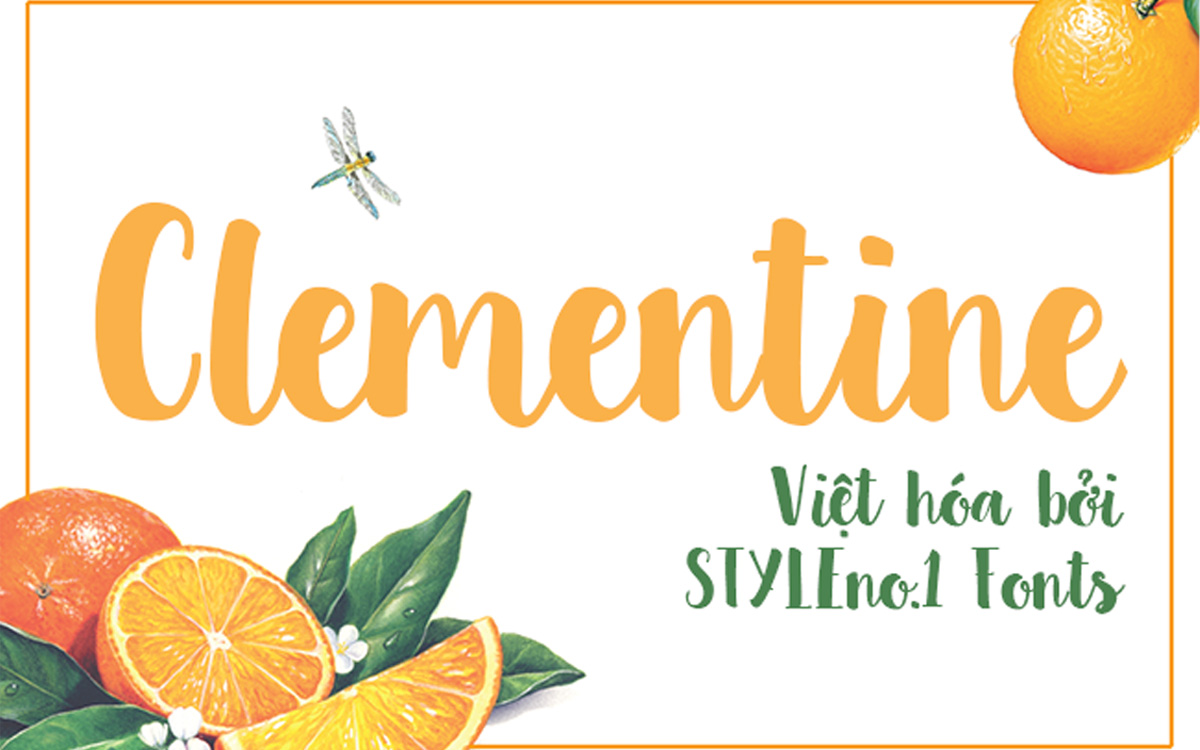
Font chữ vui vẻ, dễ thương, hoạt hình cho lĩnh vực trẻ em, đồ ăn, fodd, cute SVN-Clementine
Trong thế giới thiết kế đồ họa hiện đại, việc lựa chọn một font chữ phù hợp đóng vai trò quyết định đến cảm xúc và thông điệp mà thương hiệu muốn gửi gắm đến khách hàng. Nếu bạn đang tìm kiếm một làn gió mới tràn đầy sức sống, ngộ nghĩnh và gần gũi cho các dự án của mình thì SVN-Clementine chính là sự lựa chọn không thể tuyệt vời hơn. Với phong cách hoạt hình vui nhộn, nét chữ mềm mại cùng bản Việt hóa chỉn chu, bộ font này hứa hẹn sẽ biến mọi ý tưởng thiết kế trở nên nổi bật và đầy sức hút.
Font Chữ Vui Vẻ, Dễ Thương, Hoạt Hình Cho Lĩnh Vực Trẻ Em, Đồ Ăn (Food) – Bộ Ký Tự Cute SVN-Clementine Việt Hóa
Phong Cách Thiết Kế Bo Tròn Ngộ Nghĩnh Mang Đến Cảm Giác Vui Vẻ Tự Nhiên
Font chữ SVN-Clementine sở hữu đường nét bo tròn mượt mà, loại bỏ hoàn toàn sự cứng nhắc của các phông chữ hình học truyền thống. Sự kết hợp tinh tế giữa phong cách vẽ tay thủ công (hand-drawn) và hiệu ứng nảy (bouncy baseline) tạo nên nhịp điệu thị giác vô cùng sinh động. Mỗi ký tự trong bộ font đều được chăm chút tỉ mỉ với khoảng hở và độ dày nét hài hòa, mang đến cảm giác thân thiện, tươi vui và tràn đầy năng lượng tích cực. Phong cách hoạt hình đáng yêu này không chỉ thu hút thị giác của trẻ em mà còn dễ dàng chiếm được cảm tình của bất kỳ ai yêu thích sự ngọt ngào, gần gũi.
Điểm đặc biệt của SVN-Clementine nằm ở khả năng tạo điểm nhấn thị giác cực mạnh ngay cả khi xuất hiện ở kích thước lớn trên các bảng hiệu hay tiêu đề chính. Nét chữ đậm vừa phải cùng các góc bo tròn mượt mà giúp nội dung nổi bật mà không gây cảm giác nặng nề. Nhờ sự linh hoạt này, nhà thiết kế có thể dễ dàng phối hợp font với nhiều hiệu ứng màu sắc rực rỡ, đường viền (stroke) hoặc hiệu ứng đổ bóng (drop shadow) để tạo nên những sản phẩm truyền thông độc đáo, bắt mắt.
Việt Hóa Trọn Bộ Chuẩn Xác – Tối Ưu Cho Sáng Tạo Nội Dung Tiếng Việt
Một trong những rào cản lớn nhất khi sử dụng các font chữ cute quốc tế là lỗi hiển thị tiếng Việt như bị mất dấu, lệch dấu hoặc các ký tự có dấu bị biến dạng làm mất tính thẩm mỹ của thiết kế. SVN-Clementine đã được việt hóa hoàn chỉnh và cẩn thận đến từng chi tiết nhỏ nhất. Các dấu thanh (sắc, huyền, hỏi, ngã, nặng) và dấu mũ (â, ê, ô, ơ, ư) đều được điều chỉnh vị trí chuẩn xác, giữ nguyên tỉ lệ và tinh thần vui tươi nguyên bản của tác giả gốc.
Việc việt hóa chuẩn chỉnh giúp các nhà thiết kế đồ họa, content creator và marketer tại Việt Nam dễ dàng sáng tạo nội dung mà không gặp bất kỳ trở ngại nào về mặt kỹ thuật. Bạn có thể tự tin áp dụng SVN-Clementine vào các dự án commercial, từ viết slogan ngắn gọn, giật gân cho đến việc làm tiêu đề bài viết trên mạng xã hội, đảm bảo sự chuyên nghiệp và tính thẩm mỹ đồng nhất trên mọi ấn phẩm.
Giải Pháp Typography Lý Tưởng Cho Lĩnh Vực Trẻ Em Và Giáo Dục Mầm Non
Trẻ em luôn bị thu hút bởi những hình ảnh vui nhộn, nhiều màu sắc và những đường nét chữ ngộ nghĩnh. SVN-Clementine đáp ứng hoàn hảo yêu cầu tâm lý học thị giác này nhờ vẻ ngoài đậm chất cartoon hoạt hình. Bộ font chữ này là giải pháp typography hàng đầu cho các thương hiệu đồ chơi, thời trang trẻ em, sách truyện tranh, bìa sách giáo trình mầm non, bảng cửu chương, tập tô màu hay các khu vui chơi giải trí dành cho gia đình.
Bên cạnh đó, các ấn phẩm sự kiện như tiệc sinh nhật, Tết Trung Thu, Quốc tế Thiếu nhi hay lễ hội trường học khi ứng dụng font SVN-Clementine đều mang lại không khí hân hoan, rộn rã. Sự xuất hiện của bộ phông chữ dễ thương này trên bao bì sản phẩm mẹ và bé không chỉ gây chú ý mạnh mẽ với các bé mà còn tạo cảm giác an toàn, thân thiện và đáng tin cậy đối với các bậc phụ huynh.
Bứt Phá Sáng Tạo Trong Lĩnh Vực Đồ Ăn, Thức Uống (Food & Beverage – F&B)
Không chỉ dừng lại ở thế giới của trẻ thơ, SVN-Clementine còn phát huy sức mạnh vượt trội trong ngành ẩm thực và dịch vụ ăn uống. Nhờ kiểu dáng tròn trịa, mập mạp gợi liên tưởng đến những chiếc bánh quy bơ ngọt ngào hay những viên kẹo dẻo rực rỡ, font chữ này cực kỳ thích hợp cho các thương hiệu tiệm bánh (bakery), quán trà sữa, cửa hàng kem, quán ăn vặt và thực phẩm đóng gói. Nét chữ vui nhộn giúp kích thích vị giác và tạo nên cảm giác thèm ăn một cách rất tự nhiên.
Các designer có thể dễ dàng ứng dụng SVN-Clementine để thiết kế menu đồ ăn, tem dán ly trà sữa, bao bì hộp bánh, bảng hiệu quán ăn hay các bài đăng quảng cáo món mới trên các nền tảng mạng xã hội như Facebook, Instagram, TikTok. Tinh thần trẻ trung của font chữ giúp thương hiệu F&B truyền tải thông điệp về sự tươi ngon, niềm vui và trải nghiệm ẩm thực tuyệt vời đến với đối tượng khách hàng trẻ tuổi.